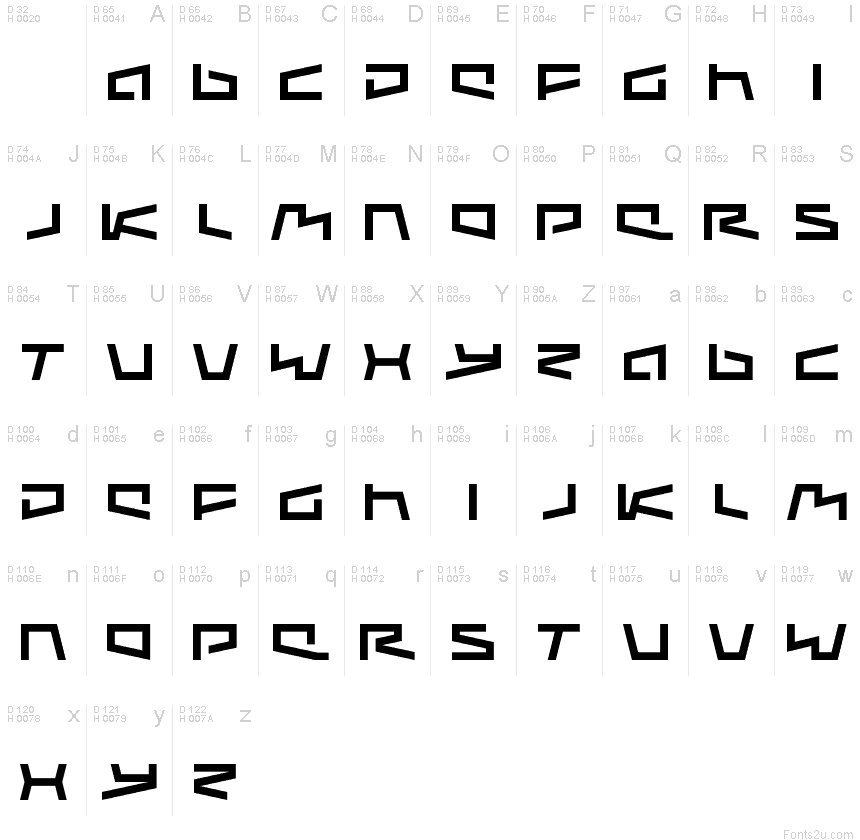
خط Augmented من تصميم Axel Pfaender هو خط عرض تقني (Techno) مجاني يبدو وكأنه قُطع من لوح معدني مصقول. بُني كل حرف من زوايا حادة ومتدرجة وخطوط مستقيمة، مما يمنح كلماتك طابعاً ميكانيكياً سريعاً وخاطفاً. إيقاع أشكاله المتعرجة يخلق شعوراً بالحركة، وكأن النص ينزلق عبر شبكة رقمية.
يتألق هذا الخط المجاني في عناوين الخيال العلمي، وشعارات الألعاب، ومنشورات موسيقى EDM وتكنو، والرسوم المتحركة، وعناوين واجهات المستخدم، وتصاميم الملابس الجريئة. استخدم Augmented بأحجام كبيرة مع تباعد واسع للحفاظ على حدة ووضوح قصاته الهندسية. بالنسبة للنص الأساسي، قم بدمجه مع خط بلا زوائد (Sans Serif) بسيط لتترك المجال لـ Augmented ليبرز في اللحظات التي تتطلب تأثيراً قوياً.